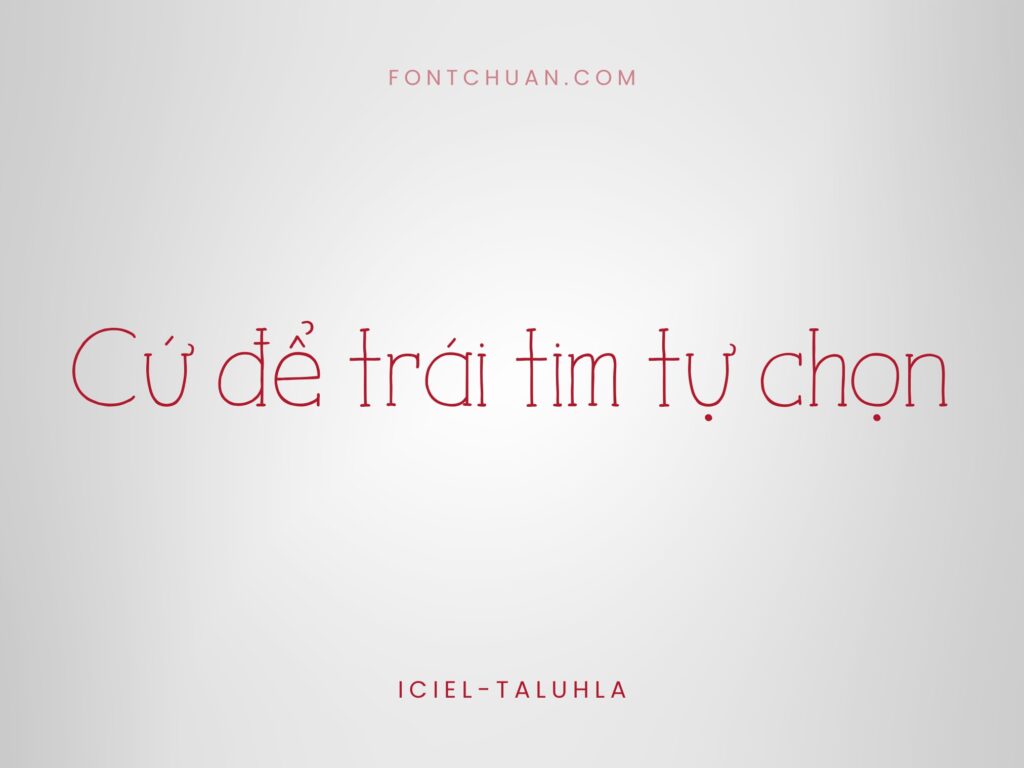
Font iCiel Taluhla Việt Hóa
Việt hóa bởi: Iciel
TALUHLA là một kiểu chữ viết tay độc đáo, mang phong cách vui tươi và sáng tạo. Được thiết kế với các ký tự cao, hẹp và hơi nghiêng, font này tạo cảm giác thân thiện và năng động cho người xem. Đặc biệt, TALUHLA đã được Việt hóa bởi iCiel, hỗ trợ tiếng Việt cùng nhiều ngôn ngữ khác, đáp ứng nhu cầu đa dạng của người dùng. Font này được chia sẻ trên các trang web như FFonts.net, giúp cộng đồng thiết kế ứng dụng dễ dàng trong các dự án của mình.
Về đặc điểm thiết kế, TALUHLA sở hữu 483 ký tự với các đường nét không đồng đều, tạo nên sự độc đáo và cá tính. Font này phù hợp cho các dự án thiết kế như thiệp mời, logo, tiêu đề, poster và bao bì sản phẩm cần sự sáng tạo và nổi bật. Ngoài ra, TALUHLA còn thích hợp cho các ngành nghề như quảng cáo, ẩm thực, thiệp cưới và spa, cùng các sự kiện đặc biệt như lễ hội, sinh nhật, Valentine và Trung thu.